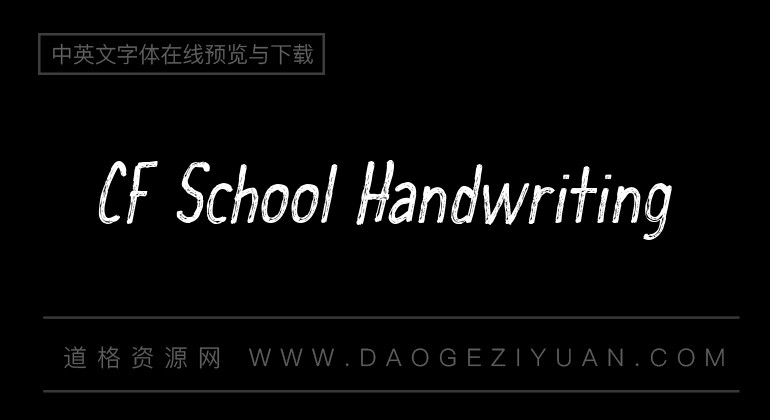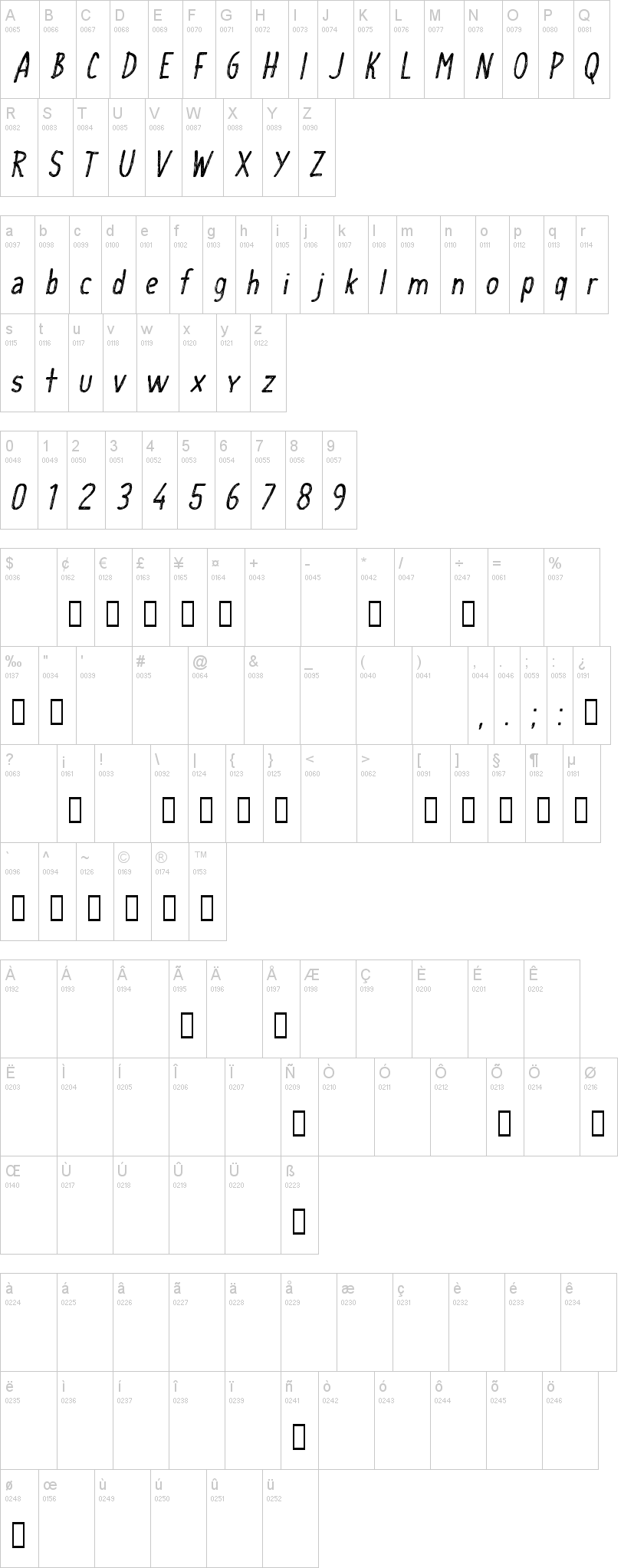
CF School Handwriting
CF School Handwriting 是一款清新活泼的手写体字体,它的特点是笔画挺拔有力,笔画间距较大,使用起来更加轻松顺畅。字形简洁,笔画粗细均匀,给人一种活泼又清新的感觉。此外,它还具备较强的可读性,可以帮助提高文字的可视性。
CF School Handwriting是一款非常不错的手写艺术字体,具有很好的视觉感,适合于文化类的宣传设计、商业类品牌的广告和产品包装设计以及个性化文字排版等较多场景。
CF School Handwriting字符映射图